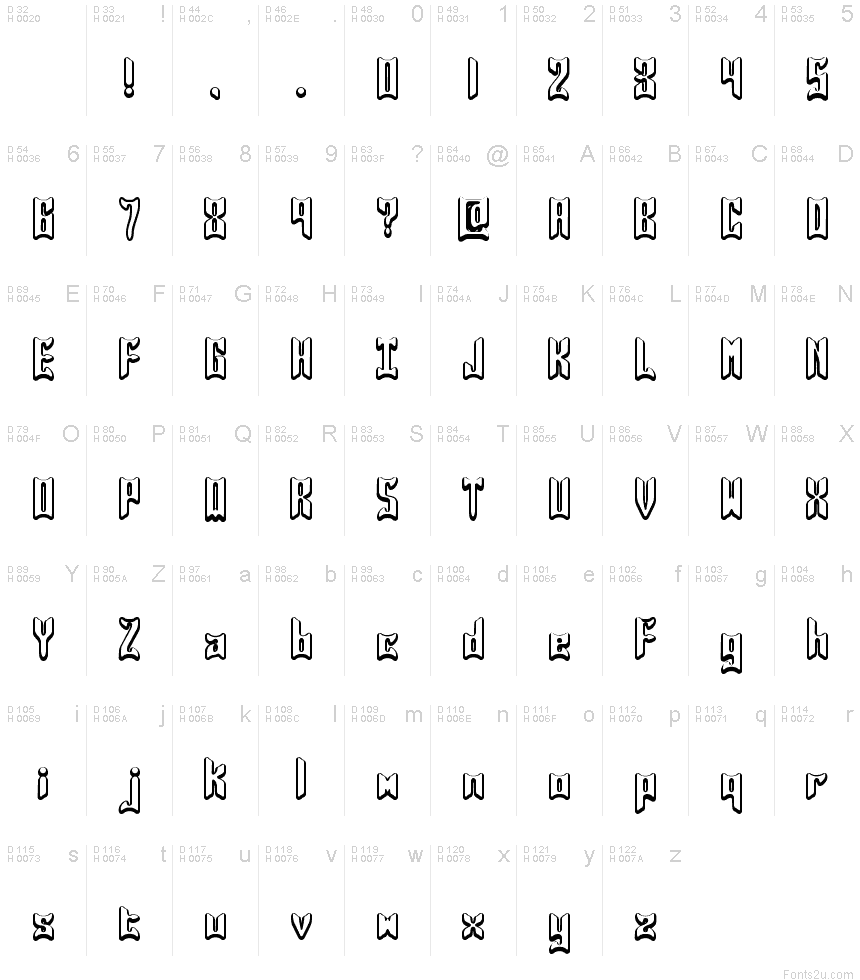
Jasper di Ænigma Fonts è un carattere display gotico moderno e gratuito, dal sapore underground e colante. I contorni neri e spessi avvolgono forme morbide e rigonfie, facendo sembrare che ogni parola sia colata sulla pagina. Le forme ricordano un mix tra un tag graffiti e un logo horror, con verticali squadrate che mantengono il caos leggibile anche a colpo d'occhio.
Con Jasper, i titoli risultano subito crudi, forti e leggermente inquietanti: ideale per locandine di film horror, volantini per eventi di Halloween, grafiche per concerti underground, loghi di videogiochi, fanzine e adesivi d'impatto. Questo font gratuito dà il meglio di sé in grandi dimensioni, dove i suoi contorni inchiostrati e le curve massicce possono respirare. Per il testo principale o i piccoli dettagli, abbinalo a un carattere sans serif pulito, così Jasper gestirà l'attitudine mentre il testo di supporto rimarrà nitido e semplice.